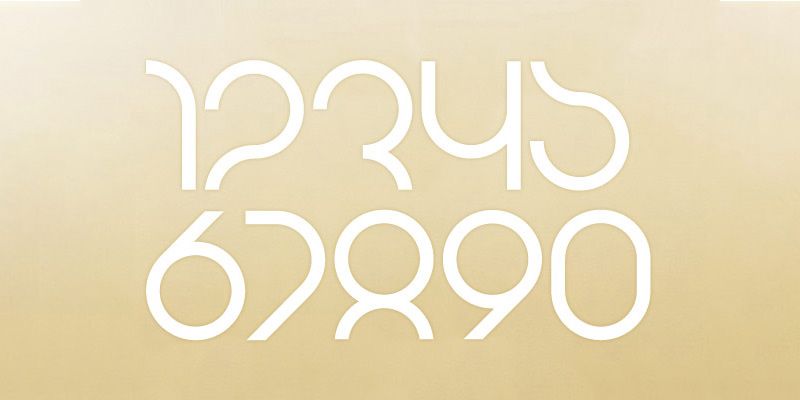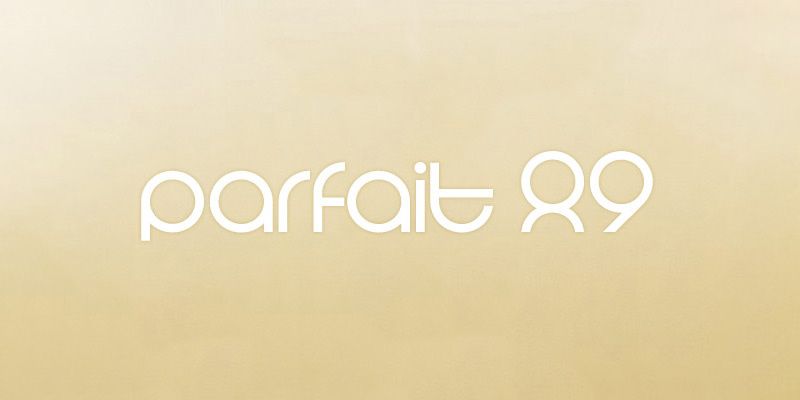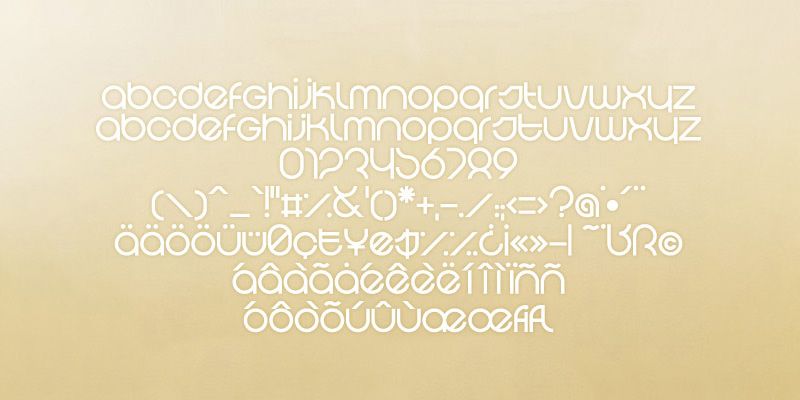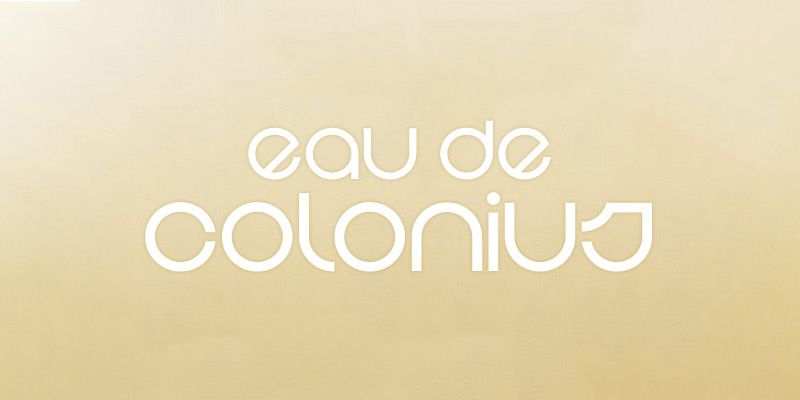
BD Colonius es una fuente de cartelería elegante y con forma redondeada. Diseñada por Lopetz en 2001.
Buro Destruct
El estudio de diseño gráfico suizo “Büro Destruct“ lo fundó en 1994 en Berna “HGB Fideljus“ Berger y Lorenz “Lopetz“ Gianfreda. En 1995 Marc “MB“ Brunner & Heinz “H1“ Reber se unió al grupo actual. En los años siguientes, Büro Destruct se convirtió en un estudio de diseño multidisciplinario reconocido internacionalmente. Desde 1995, Büro Destruct publica fuentes de su casa tipográfica “Typedifferent.com“. Como se desprende del nombre “Typedifferent“, las fuentes de Büro Destruct son principalmente tipos de letra con características de letras únicas. Aparecen en numerosas fundas de discos, revistas, créditos de películas y televisión, impresiones de moda y sitios web.